Cover podcast có một đặc thù rất dễ bị xem nhẹ: người nghe thường nhìn thấy nó ở kích thước rất nhỏ trên Spotify, Apple Podcasts, YouTube, Facebook hoặc trong danh sách gợi ý. Vì vậy, font cho podcast cover không chỉ cần đẹp khi mở lớn, mà còn phải đọc được nhanh trong thumbnail vuông. Tên show, tên host và chủ đề tập cần có thứ bậc rõ ràng, nếu không cover sẽ đẹp nhưng khó nhớ.
Bài viết này gợi ý 15 font TH Việt hóa phù hợp cho podcast cover, audio show, kênh nội dung cá nhân và creator branding. Danh sách ưu tiên font sans-serif sạch, display nhẹ, font viết tay/script có cảm xúc và một vài lựa chọn trẻ trung cho kênh giải trí. Khi chọn font, anh nên nghĩ theo hệ thống: một font chính cho tên show, một font phụ cho mô tả/tập phát sóng và một kiểu chữ điểm nhấn cho chữ ký host hoặc slogan.
Tiêu chí chọn font podcast cover
Font tốt cho podcast cần vượt qua ba bài kiểm tra. Thứ nhất là độ đọc ở kích thước nhỏ: các cụm như “Tập 12”, “Chuyện nghề”, “Đọc sách cùng tôi”, “Hỏi đáp cuối tuần” phải rõ ngay cả khi thu nhỏ. Thứ hai là đúng giọng nội dung: podcast tài chính cần khác podcast healing, show phỏng vấn cần khác kênh giải trí. Thứ ba là hỗ trợ tiếng Việt có dấu, vì cover thường dùng ít chữ nhưng chữ nào cũng phải chuẩn.
Top 15 font TH cho podcast cover và creator branding
1. TH Legacy Sans - podcast kinh doanh, kiến thức, self-growth và kênh chuyên gia
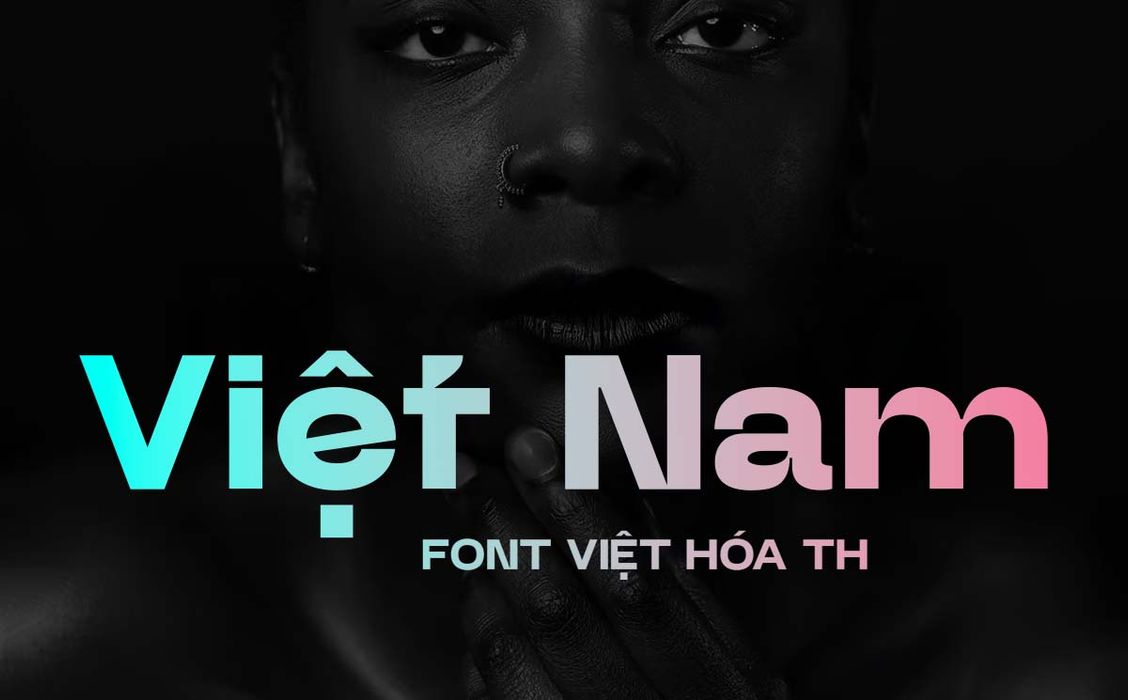
Tải font TH Legacy Sans nếu anh đang làm podcast kinh doanh, kiến thức, self-growth và kênh chuyên gia. Điểm mạnh của TH Legacy Sans là sạch, hiện đại, dễ đọc khi thu nhỏ cover xuống kích thước thumbnail. Với podcast cover, font này nên được test trên bố cục vuông 1:1, trong đó tên show chiếm khoảng 35-50% diện tích chữ, còn tên host hoặc tagline nhỏ hơn để không tranh sự chú ý.
Khi phối với ảnh chân dung hoặc nền minh họa, anh nên giữ tương phản rõ giữa chữ và nền. Nếu dùng TH Legacy Sans cho tên show, phần mô tả tập nên chuyển sang một font sans-serif gọn hơn hoặc giảm hiệu ứng để cover không bị quá nhiều tiếng nói thị giác.
2. TH Guton - cover podcast có nhiều cấp chữ, series dài tập và branding creator
Tải font TH Guton nếu anh đang làm cover podcast có nhiều cấp chữ, series dài tập và branding creator. Điểm mạnh của TH Guton là có nhiều style nên rất tiện để phân cấp tên show, tên tập và tên host. Với podcast cover, font này nên được test trên bố cục vuông 1:1, trong đó tên show chiếm khoảng 35-50% diện tích chữ, còn tên host hoặc tagline nhỏ hơn để không tranh sự chú ý.
Khi phối với ảnh chân dung hoặc nền minh họa, anh nên giữ tương phản rõ giữa chữ và nền. Nếu dùng TH Guton cho tên show, phần mô tả tập nên chuyển sang một font sans-serif gọn hơn hoặc giảm hiệu ứng để cover không bị quá nhiều tiếng nói thị giác.
3. TH Cameo Sans - podcast lifestyle, phỏng vấn, giáo dục nhẹ nhàng và personal brand
Tải font TH Cameo Sans nếu anh đang làm podcast lifestyle, phỏng vấn, giáo dục nhẹ nhàng và personal brand. Điểm mạnh của TH Cameo Sans là thanh lịch, cân bằng giữa cảm giác thân thiện và chuyên nghiệp. Với podcast cover, font này nên được test trên bố cục vuông 1:1, trong đó tên show chiếm khoảng 35-50% diện tích chữ, còn tên host hoặc tagline nhỏ hơn để không tranh sự chú ý.
Khi phối với ảnh chân dung hoặc nền minh họa, anh nên giữ tương phản rõ giữa chữ và nền. Nếu dùng TH Cameo Sans cho tên show, phần mô tả tập nên chuyển sang một font sans-serif gọn hơn hoặc giảm hiệu ứng để cover không bị quá nhiều tiếng nói thị giác.
4. TH Manisans - audio show cao cấp, nội dung tài chính, tư duy và thương hiệu cá nhân
Tải font TH Manisans nếu anh đang làm audio show cao cấp, nội dung tài chính, tư duy và thương hiệu cá nhân. Điểm mạnh của TH Manisans là hiện đại nhưng vẫn có độ sang, hợp với cover tối giản. Với podcast cover, font này nên được test trên bố cục vuông 1:1, trong đó tên show chiếm khoảng 35-50% diện tích chữ, còn tên host hoặc tagline nhỏ hơn để không tranh sự chú ý.
Khi phối với ảnh chân dung hoặc nền minh họa, anh nên giữ tương phản rõ giữa chữ và nền. Nếu dùng TH Manisans cho tên show, phần mô tả tập nên chuyển sang một font sans-serif gọn hơn hoặc giảm hiệu ứng để cover không bị quá nhiều tiếng nói thị giác.
5. TH Cemains - podcast chữa lành, giáo dục, cộng đồng và kênh chia sẻ kiến thức
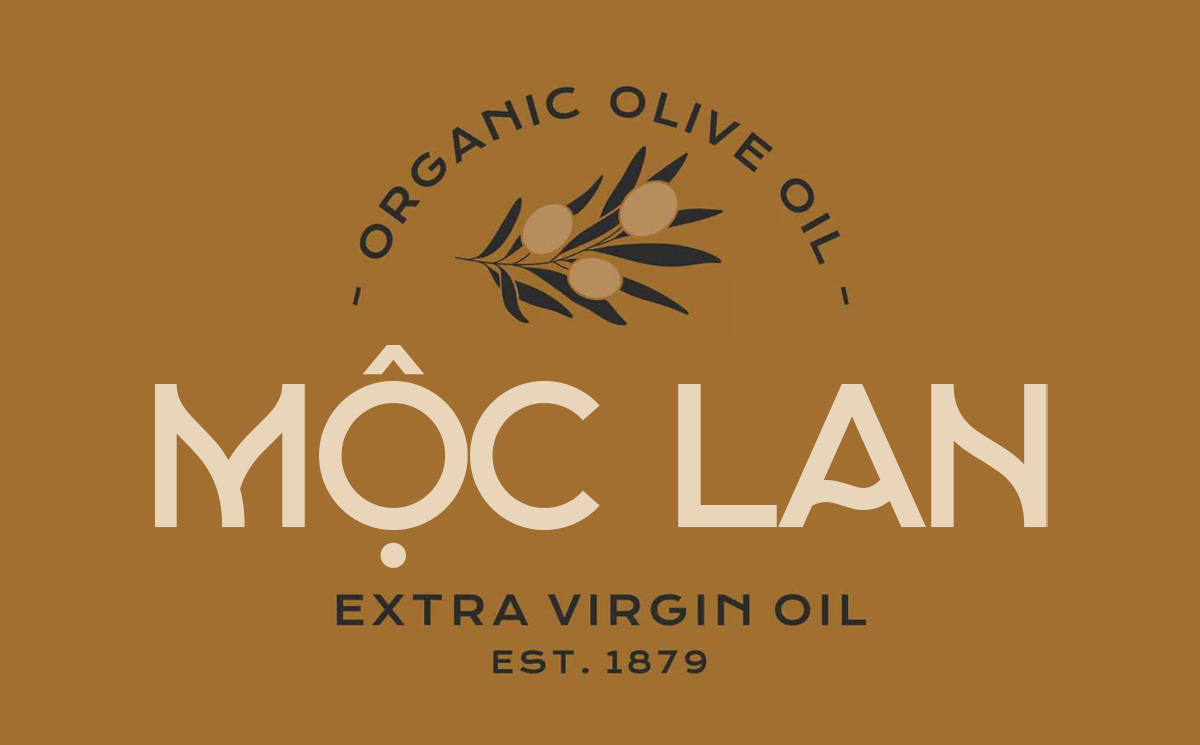
Tải font TH Cemains nếu anh đang làm podcast chữa lành, giáo dục, cộng đồng và kênh chia sẻ kiến thức. Điểm mạnh của TH Cemains là mềm hơn nhóm sans mạnh, tạo cảm giác dễ nghe và đáng tin. Với podcast cover, font này nên được test trên bố cục vuông 1:1, trong đó tên show chiếm khoảng 35-50% diện tích chữ, còn tên host hoặc tagline nhỏ hơn để không tranh sự chú ý.
Khi phối với ảnh chân dung hoặc nền minh họa, anh nên giữ tương phản rõ giữa chữ và nền. Nếu dùng TH Cemains cho tên show, phần mô tả tập nên chuyển sang một font sans-serif gọn hơn hoặc giảm hiệu ứng để cover không bị quá nhiều tiếng nói thị giác.
6. TH Okaba - cover show cá nhân, talkshow sáng tạo và nội dung thương hiệu
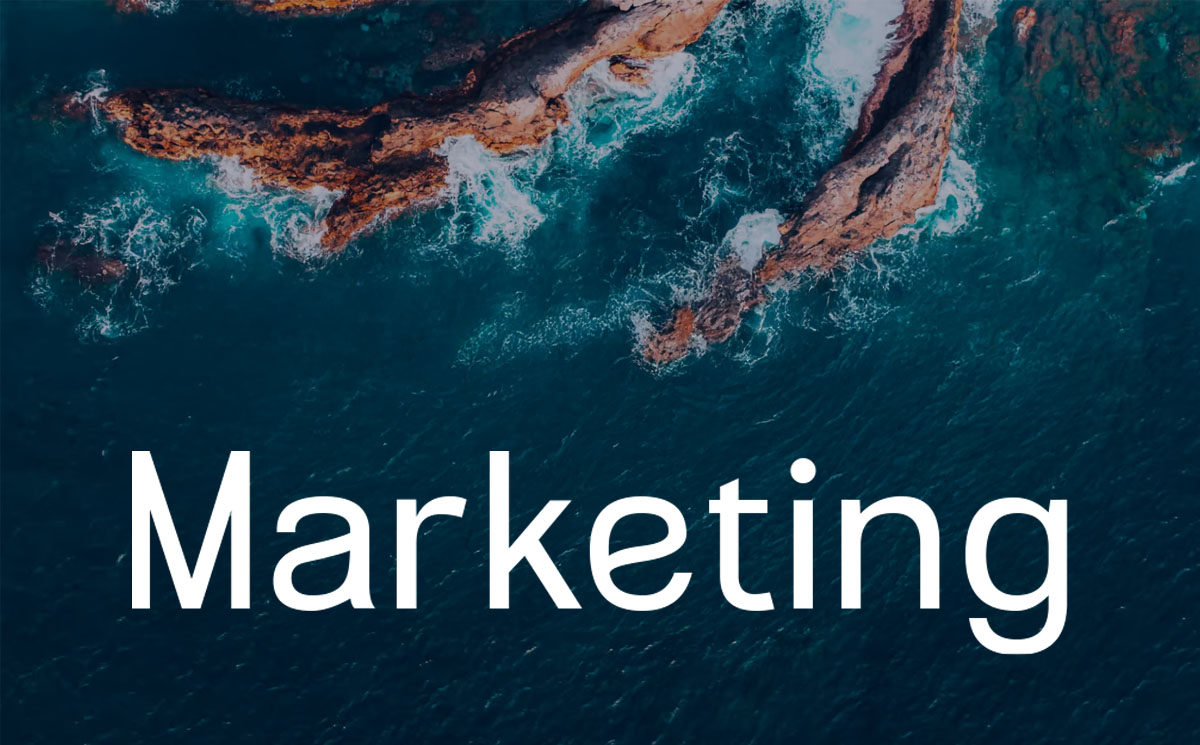
Tải font TH Okaba nếu anh đang làm cover show cá nhân, talkshow sáng tạo và nội dung thương hiệu. Điểm mạnh của TH Okaba là có tinh thần boutique, hợp khi muốn hình ảnh creator nhìn chỉn chu. Với podcast cover, font này nên được test trên bố cục vuông 1:1, trong đó tên show chiếm khoảng 35-50% diện tích chữ, còn tên host hoặc tagline nhỏ hơn để không tranh sự chú ý.
Khi phối với ảnh chân dung hoặc nền minh họa, anh nên giữ tương phản rõ giữa chữ và nền. Nếu dùng TH Okaba cho tên show, phần mô tả tập nên chuyển sang một font sans-serif gọn hơn hoặc giảm hiệu ứng để cover không bị quá nhiều tiếng nói thị giác.
7. TH Minoruca - podcast nghệ thuật, văn hóa, thời trang và show kể chuyện
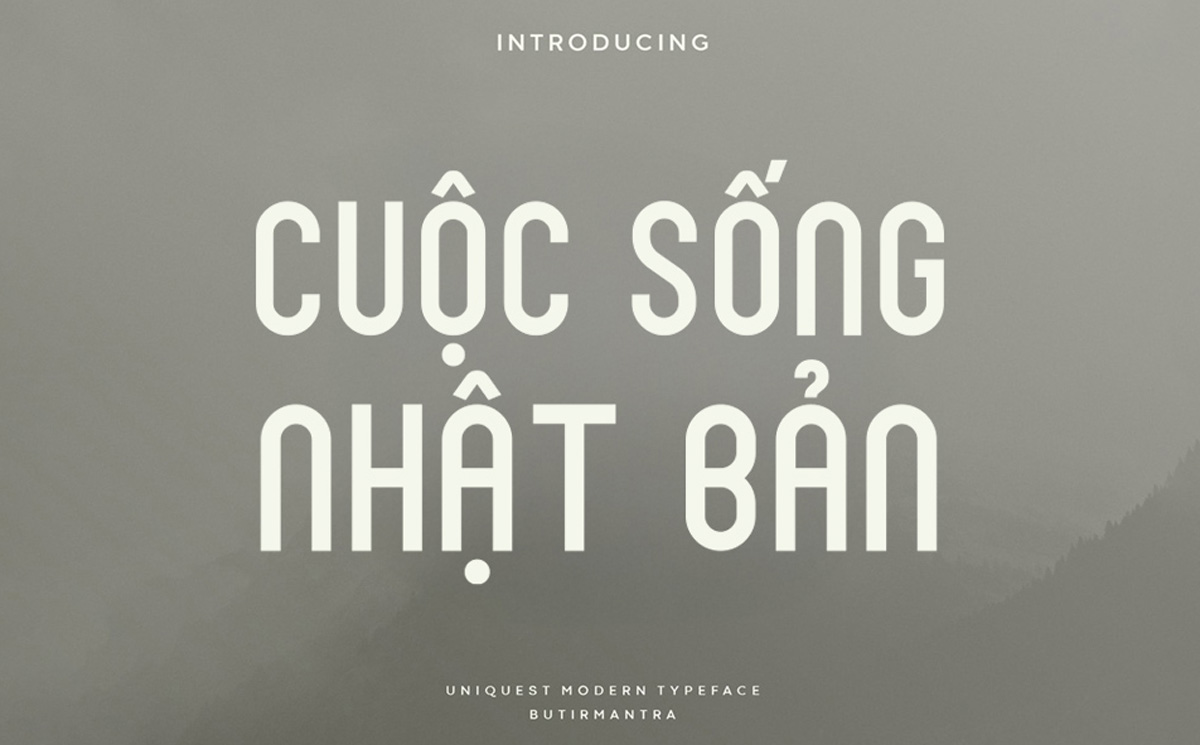
Tải font TH Minoruca nếu anh đang làm podcast nghệ thuật, văn hóa, thời trang và show kể chuyện. Điểm mạnh của TH Minoruca là mang cảm giác thanh lịch, phù hợp với cover có ảnh chân dung hoặc bố cục tối giản. Với podcast cover, font này nên được test trên bố cục vuông 1:1, trong đó tên show chiếm khoảng 35-50% diện tích chữ, còn tên host hoặc tagline nhỏ hơn để không tranh sự chú ý.
Khi phối với ảnh chân dung hoặc nền minh họa, anh nên giữ tương phản rõ giữa chữ và nền. Nếu dùng TH Minoruca cho tên show, phần mô tả tập nên chuyển sang một font sans-serif gọn hơn hoặc giảm hiệu ứng để cover không bị quá nhiều tiếng nói thị giác.
8. TH Glafty - podcast Gen Z, giải trí, review, pop culture và kênh nội dung năng động
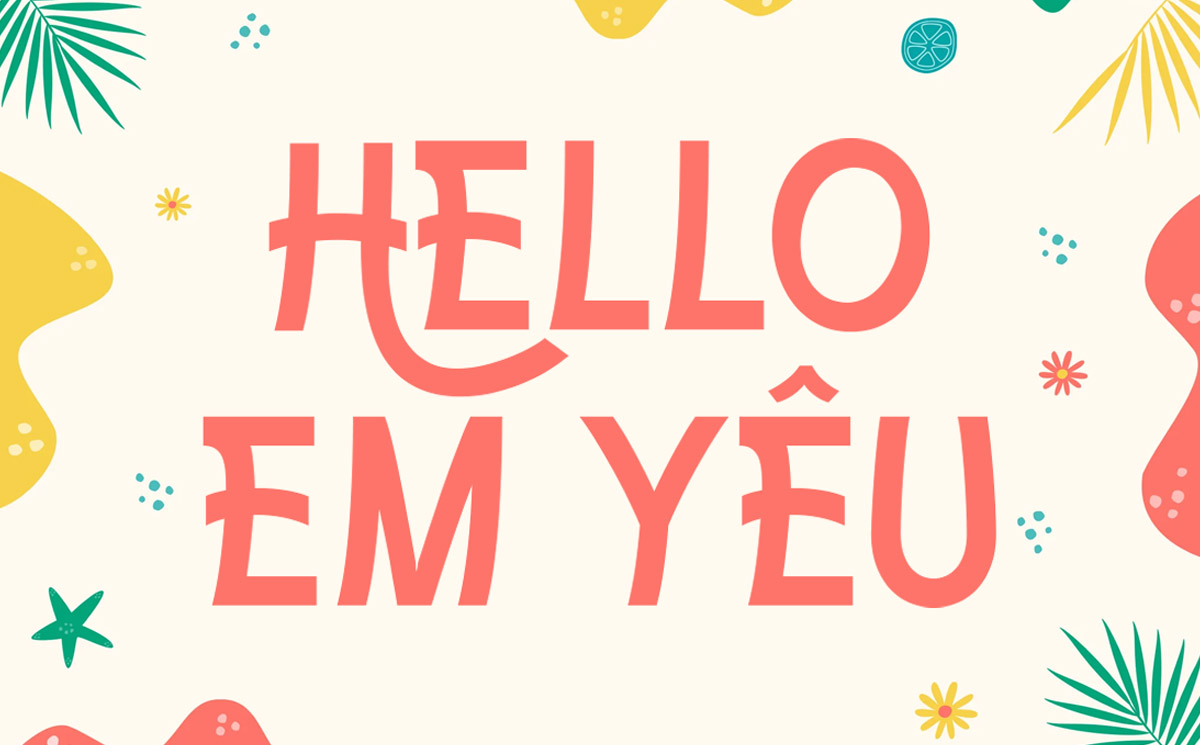
Tải font TH Glafty nếu anh đang làm podcast Gen Z, giải trí, review, pop culture và kênh nội dung năng động. Điểm mạnh của TH Glafty là vui, trẻ và dễ tạo điểm nhấn cho tên show. Với podcast cover, font này nên được test trên bố cục vuông 1:1, trong đó tên show chiếm khoảng 35-50% diện tích chữ, còn tên host hoặc tagline nhỏ hơn để không tranh sự chú ý.
Khi phối với ảnh chân dung hoặc nền minh họa, anh nên giữ tương phản rõ giữa chữ và nền. Nếu dùng TH Glafty cho tên show, phần mô tả tập nên chuyển sang một font sans-serif gọn hơn hoặc giảm hiệu ứng để cover không bị quá nhiều tiếng nói thị giác.
9. TH Monday Feelings - show tâm sự, nhật ký âm thanh, podcast đời sống và nội dung cozy
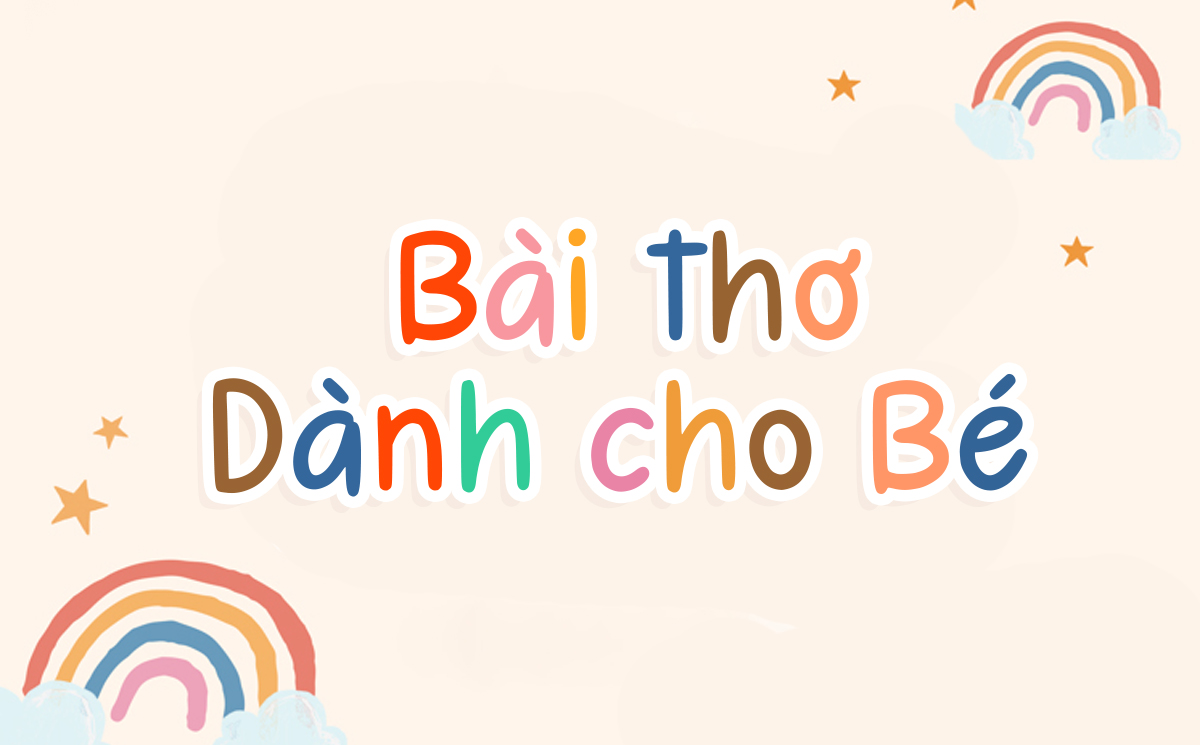
Tải font TH Monday Feelings nếu anh đang làm show tâm sự, nhật ký âm thanh, podcast đời sống và nội dung cozy. Điểm mạnh của TH Monday Feelings là cute vừa đủ, tạo cảm giác gần gũi như một cuộc trò chuyện riêng. Với podcast cover, font này nên được test trên bố cục vuông 1:1, trong đó tên show chiếm khoảng 35-50% diện tích chữ, còn tên host hoặc tagline nhỏ hơn để không tranh sự chú ý.
Khi phối với ảnh chân dung hoặc nền minh họa, anh nên giữ tương phản rõ giữa chữ và nền. Nếu dùng TH Monday Feelings cho tên show, phần mô tả tập nên chuyển sang một font sans-serif gọn hơn hoặc giảm hiệu ứng để cover không bị quá nhiều tiếng nói thị giác.
10. TH Sophia Melanie - podcast gia đình, giáo dục trẻ em, mẹ và bé hoặc show vui vẻ
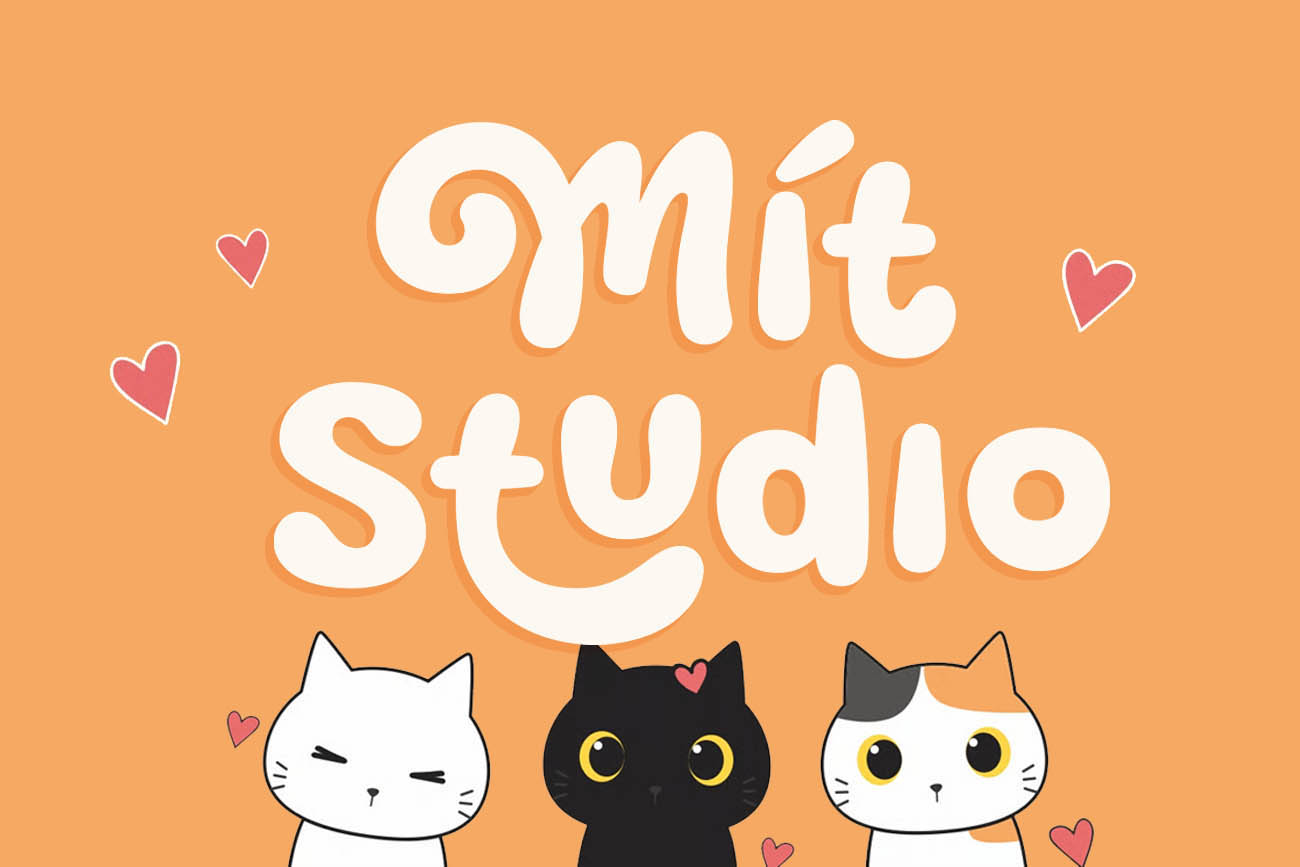
Tải font TH Sophia Melanie nếu anh đang làm podcast gia đình, giáo dục trẻ em, mẹ và bé hoặc show vui vẻ. Điểm mạnh của TH Sophia Melanie là tròn trịa, thân thiện, dễ làm cover có cảm xúc tích cực. Với podcast cover, font này nên được test trên bố cục vuông 1:1, trong đó tên show chiếm khoảng 35-50% diện tích chữ, còn tên host hoặc tagline nhỏ hơn để không tranh sự chú ý.
Khi phối với ảnh chân dung hoặc nền minh họa, anh nên giữ tương phản rõ giữa chữ và nền. Nếu dùng TH Sophia Melanie cho tên show, phần mô tả tập nên chuyển sang một font sans-serif gọn hơn hoặc giảm hiệu ứng để cover không bị quá nhiều tiếng nói thị giác.
11. TH Cherry Feeling - podcast cá nhân, nhật ký sáng tạo, kênh học tập và lifestyle mềm mại
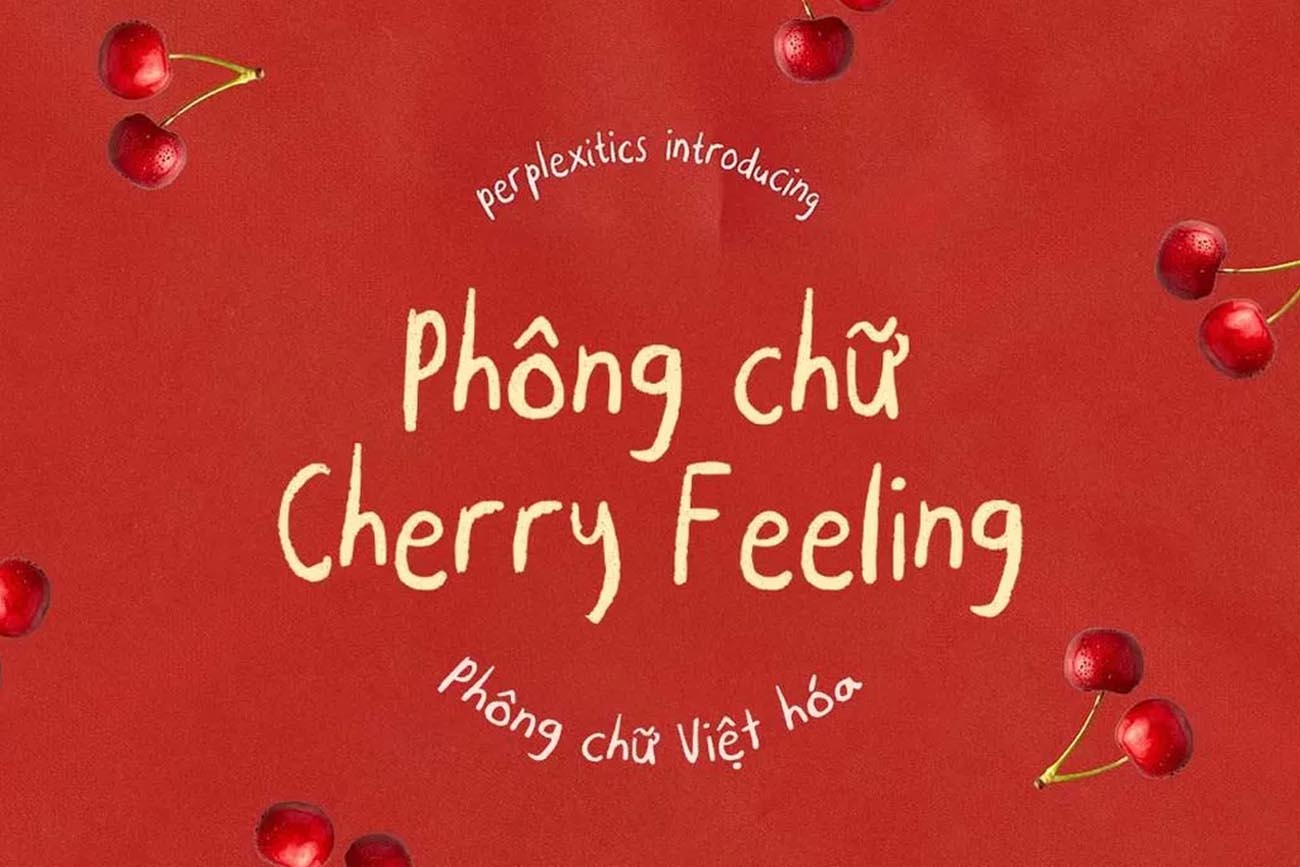
Tải font TH Cherry Feeling nếu anh đang làm podcast cá nhân, nhật ký sáng tạo, kênh học tập và lifestyle mềm mại. Điểm mạnh của TH Cherry Feeling là viết tay dễ thương, hợp làm điểm nhấn phụ hoặc tên series ngắn. Với podcast cover, font này nên được test trên bố cục vuông 1:1, trong đó tên show chiếm khoảng 35-50% diện tích chữ, còn tên host hoặc tagline nhỏ hơn để không tranh sự chú ý.
Khi phối với ảnh chân dung hoặc nền minh họa, anh nên giữ tương phản rõ giữa chữ và nền. Nếu dùng TH Cherry Feeling cho tên show, phần mô tả tập nên chuyển sang một font sans-serif gọn hơn hoặc giảm hiệu ứng để cover không bị quá nhiều tiếng nói thị giác.
12. TH Hulahoy - audio show kể chuyện, thơ, healing và nội dung cảm xúc
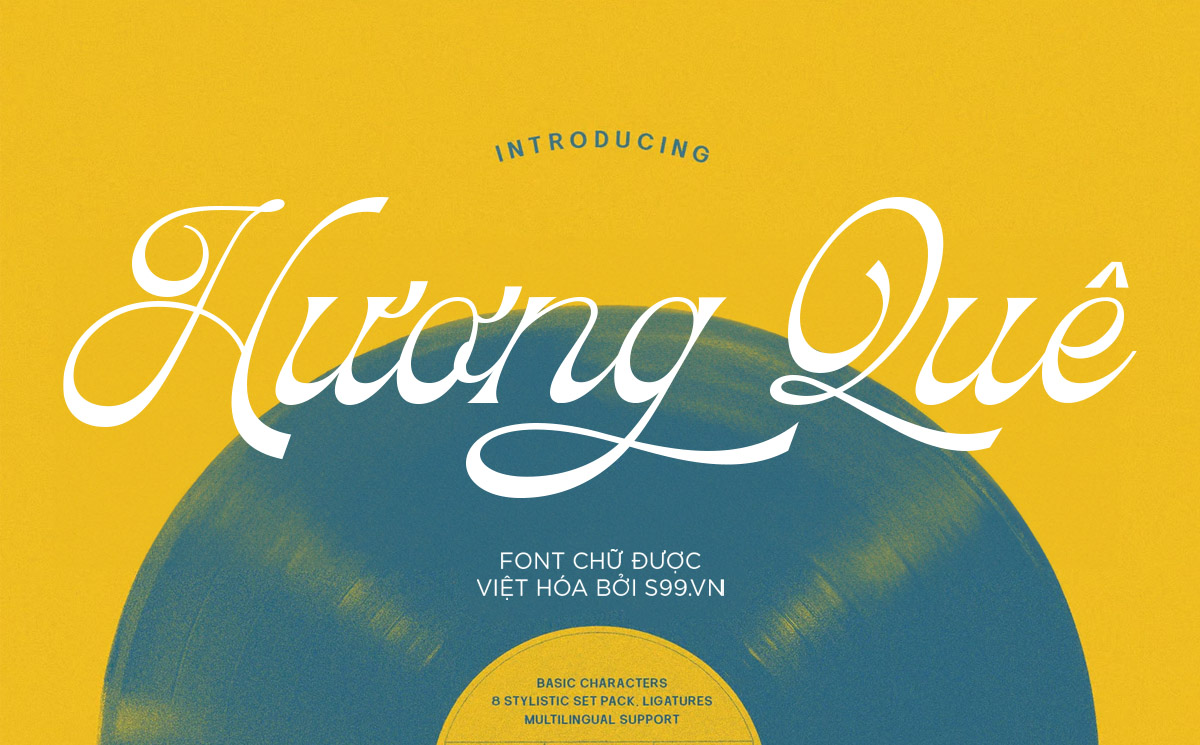
Tải font TH Hulahoy nếu anh đang làm audio show kể chuyện, thơ, healing và nội dung cảm xúc. Điểm mạnh của TH Hulahoy là nét uốn mềm, tạo chất thủ công và cảm giác riêng tư. Với podcast cover, font này nên được test trên bố cục vuông 1:1, trong đó tên show chiếm khoảng 35-50% diện tích chữ, còn tên host hoặc tagline nhỏ hơn để không tranh sự chú ý.
Khi phối với ảnh chân dung hoặc nền minh họa, anh nên giữ tương phản rõ giữa chữ và nền. Nếu dùng TH Hulahoy cho tên show, phần mô tả tập nên chuyển sang một font sans-serif gọn hơn hoặc giảm hiệu ứng để cover không bị quá nhiều tiếng nói thị giác.
13. TH Sweets Holly - personal brand creator, chữ ký host và cover có ảnh chân dung
Tải font TH Sweets Holly nếu anh đang làm personal brand creator, chữ ký host và cover có ảnh chân dung. Điểm mạnh của TH Sweets Holly là đậm chất signature, rất hợp để dùng như dấu nhận diện cá nhân. Với podcast cover, font này nên được test trên bố cục vuông 1:1, trong đó tên show chiếm khoảng 35-50% diện tích chữ, còn tên host hoặc tagline nhỏ hơn để không tranh sự chú ý.
Khi phối với ảnh chân dung hoặc nền minh họa, anh nên giữ tương phản rõ giữa chữ và nền. Nếu dùng TH Sweets Holly cho tên show, phần mô tả tập nên chuyển sang một font sans-serif gọn hơn hoặc giảm hiệu ứng để cover không bị quá nhiều tiếng nói thị giác.
14. TH Modernline - podcast phỏng vấn, creator coaching và show thương hiệu cá nhân
Tải font TH Modernline nếu anh đang làm podcast phỏng vấn, creator coaching và show thương hiệu cá nhân. Điểm mạnh của TH Modernline là tự nhiên, thanh mảnh, tạo cảm giác gần người nhưng vẫn tinh tế. Với podcast cover, font này nên được test trên bố cục vuông 1:1, trong đó tên show chiếm khoảng 35-50% diện tích chữ, còn tên host hoặc tagline nhỏ hơn để không tranh sự chú ý.
Khi phối với ảnh chân dung hoặc nền minh họa, anh nên giữ tương phản rõ giữa chữ và nền. Nếu dùng TH Modernline cho tên show, phần mô tả tập nên chuyển sang một font sans-serif gọn hơn hoặc giảm hiệu ứng để cover không bị quá nhiều tiếng nói thị giác.
15. TH Kairo - podcast retro, văn hóa đại chúng, âm nhạc và storytelling
Tải font TH Kairo nếu anh đang làm podcast retro, văn hóa đại chúng, âm nhạc và storytelling. Điểm mạnh của TH Kairo là kết hợp hiện đại với retro, giúp cover có cá tính mà không quá khó đọc. Với podcast cover, font này nên được test trên bố cục vuông 1:1, trong đó tên show chiếm khoảng 35-50% diện tích chữ, còn tên host hoặc tagline nhỏ hơn để không tranh sự chú ý.
Khi phối với ảnh chân dung hoặc nền minh họa, anh nên giữ tương phản rõ giữa chữ và nền. Nếu dùng TH Kairo cho tên show, phần mô tả tập nên chuyển sang một font sans-serif gọn hơn hoặc giảm hiệu ứng để cover không bị quá nhiều tiếng nói thị giác.
Cách phối font cho podcast cover chuyên nghiệp hơn
1. Dùng font sans-serif cho thông tin cần đọc nhanh
Những thông tin như tên tập, mùa phát sóng, số episode, tên khách mời hoặc chủ đề chính nên dùng font dễ đọc. Các font như TH Legacy Sans, TH Guton, TH Cameo Sans, TH Cemains, TH Teknaf-style tương tự trong nhóm sans sẽ giúp cover gọn hơn. Nếu show có nhiều tập và mỗi tập thay nội dung, nhóm font sạch sẽ tiết kiệm rất nhiều thời gian thiết kế.
2. Dùng font script hoặc viết tay cho dấu ấn cá nhân
Podcast cá nhân thường cần cảm giác gần gũi. Các font như TH Cherry Feeling, TH Hulahoy, TH Sweets Holly hoặc TH Modernline có thể dùng cho chữ ký host, slogan ngắn hoặc một từ khóa cảm xúc. Tuy nhiên, không nên dùng script cho toàn bộ tiêu đề dài vì chữ có dấu sẽ dễ rối khi thu nhỏ.
3. Giữ hệ thống nhận diện qua nhiều tập
Một podcast tốt không chỉ có một cover đẹp, mà cần một hệ thống cover dễ nhận ra qua nhiều tập. Anh có thể cố định font tên show, màu nền và vị trí ảnh host; chỉ thay tên tập, số tập hoặc khách mời. Cách này giúp kênh nhìn chuyên nghiệp hơn và người nghe dễ nhận diện khi lướt feed.
Gợi ý chọn nhanh theo kiểu nội dung
Nếu làm podcast chuyên gia, kinh doanh, tài chính hoặc giáo dục, hãy bắt đầu với TH Legacy Sans, TH Guton, TH Manisans hoặc TH Cameo Sans. Nếu làm show lifestyle, healing, tâm sự hoặc kể chuyện, TH Cemains, TH Minoruca, TH Monday Feelings, TH Hulahoy và TH Modernline sẽ hợp hơn. Với kênh creator trẻ, review, văn hóa đại chúng hoặc nội dung giải trí, TH Glafty, TH Sophia Melanie, TH Cherry Feeling và TH Kairo là nhóm nên thử.
Font chữ cho podcast cover cần vừa có cá tính vừa đọc rõ trên thumbnail nhỏ. Một lựa chọn đẹp trong file thiết kế chưa chắc đã hiệu quả trên app nghe podcast, vì vậy hãy luôn test cover ở kích thước nhỏ trước khi chốt. Danh sách 15 font TH trên đủ để anh triển khai nhiều hướng: chuyên nghiệp, sáng tạo, gần gũi, trẻ trung hoặc mang màu sắc cá nhân rõ nét.
Cách làm an toàn là chọn một font chính thật dễ nhớ cho tên show, một font phụ rõ ràng cho thông tin tập và một font cảm xúc cho điểm nhấn. Khi hệ thống font ổn, podcast cover sẽ nhất quán hơn, dễ nhận diện hơn và tạo cảm giác đáng nghe ngay từ lần chạm mắt đầu tiên.